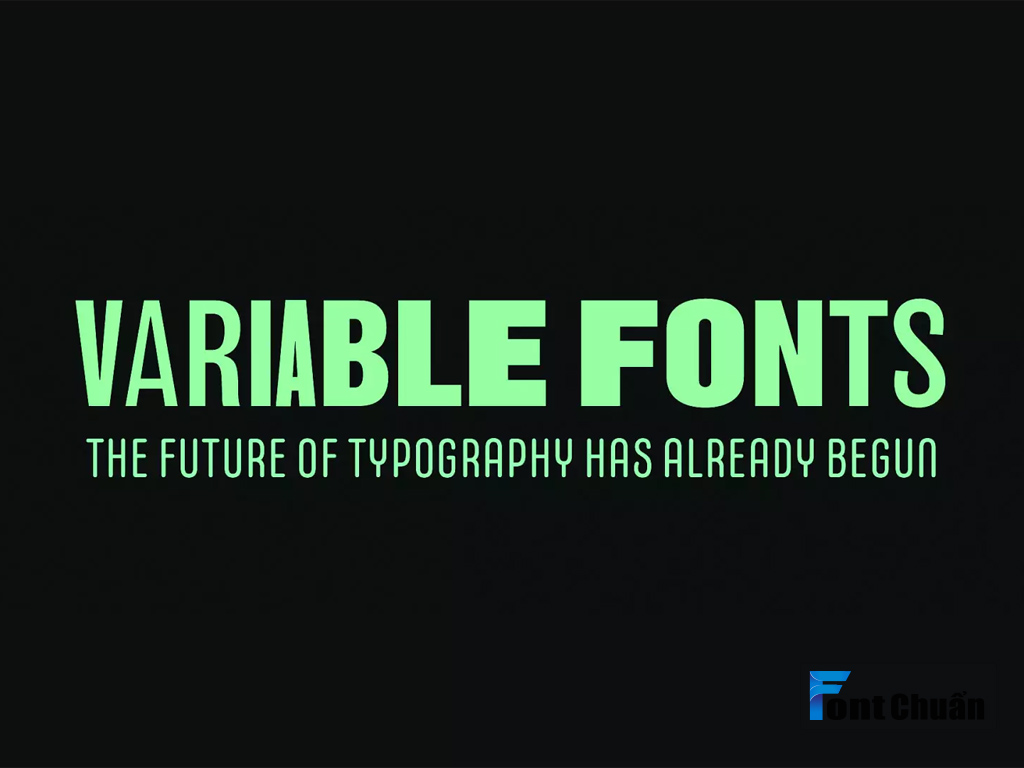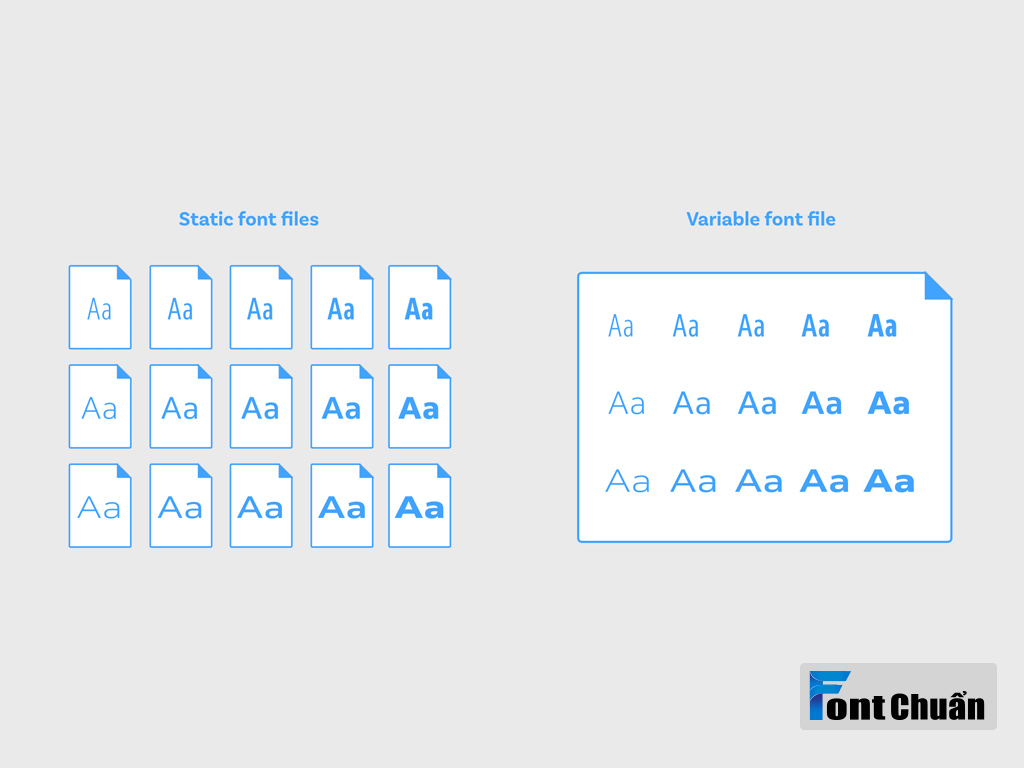
Variable Fonts cho phép tích hợp nhiều biến thể kiểu dáng như trọng lượng, độ rộng và độ nghiêng chỉ trong một tệp duy nhất, giúp tối ưu hiệu suất và linh hoạt hơn trong thiết kế. Được phát triển dựa trên chuẩn OpenType bởi Microsoft, Apple, Adobe và Google, công nghệ này mở ra tương lai mới cho responsive typography và thiết kế web hiện đại. Bài viết sau của Font Chuẩn sẽ đi sâu và tìm hiểu Variable Fonts là gì? Lợi ích, cách ứng dụng trong thiết kế, lập trình web và những lưu ý quan trọng khi triển khai.
Variable Fonts là gì? Định nghĩa chi tiết
Variable Fonts (phông chữ biến đổi) đánh dấu một bước tiến lớn của đặc tả OpenType, cho phép tích hợp nhiều biến thể kiểu dáng – như trọng lượng (weight), chiều rộng (width), độ nghiêng (slant) – chỉ trong một tệp duy nhất.
Khác với font tĩnh truyền thống yêu cầu nhiều file riêng biệt (Regular, Bold, Italic…), Variable Fonts tạo ra một phổ liên tục các phong cách, cho phép nhà thiết kế tùy chỉnh linh hoạt thông số như độ đậm chính xác (ví dụ 686/900) thay vì giới hạn ở các mức định sẵn.
Được phát triển từ sự hợp tác giữa Google, Apple, Microsoft và Adobe, công nghệ này giải quyết hạn chế cồng kềnh của font tĩnh và mở ra tương lai mới cho typography kỹ thuật số. Variable Fonts không chỉ tối ưu hiệu suất mà còn trao quyền sáng tạo mạnh mẽ hơn cho người dùng và nhà thiết kế.
Sự khác biệt giữa Variable Fonts và font tĩnh
Điểm khác biệt cơ bản giữa Variable Fonts và font tĩnh nằm ở cấu trúc tệp và khả năng biến đổi. Với font tĩnh, mỗi biến thể kiểu dáng như Regular, Bold hay Italic của một font (ví dụ Font chữ Roboto) yêu cầu tệp riêng biệt (Roboto-Regular.woff2, Roboto-Bold.woff2, Roboto-Italic.woff2). Trong khi đó, Variable Fonts như RobotoFlex.woff2 gói gọn toàn bộ biến thể vào một tệp duy nhất.
Không chỉ tối ưu về dung lượng và hiệu suất tải trang (giảm số lượng yêu cầu HTTP), Variable Fonts còn thay thế hệ thống kiểu rời rạc bằng các trục biến đổi (variation axes) như độ đậm (wght), độ rộng (wdth) và độ nghiêng (slnt). Người dùng có thể điều chỉnh linh hoạt giá trị trên các trục này, tạo ra vô số biến thể trung gian thay vì bị giới hạn ở các mức cố định.
Sự khác biệt này tác động sâu sắc đến thiết kế hiện đại:
- Hiệu suất web: Tệp gọn nhẹ, tối ưu tốc độ tải.
- Tự do sáng tạo: Dễ dàng tinh chỉnh typography theo yêu cầu thị giác.
- Responsive typography: Font thích ứng tốt hơn với kích thước và ngữ cảnh thiết bị.
- Biểu cảm typographic cao: Nhà thiết kế có thể kiểm soát tỉ mỉ độ đậm (ví dụ 451/900) hoặc chiều rộng, giúp giải quyết chính xác các vấn đề về bố cục, cân bằng hệ thống phân cấp thị giác và tối ưu trải nghiệm người dùng (UI/UX Design).
Variable Fonts không chỉ cải tiến hiệu quả kỹ thuật, mà còn mở ra một cách tiếp cận typography năng động và tích hợp sâu hơn vào thiết kế giao diện số.
Ưu điểm của việc sử dụng Variable Fonts
Việc áp dụng Variable Fonts mang lại nhiều lợi ích đáng kể so với việc sử dụng font tĩnh truyền thống, tác động tích cực đến cả hiệu suất kỹ thuật và khả năng sáng tạo trong thiết kế.
Tiết kiệm dung lượng, tăng tốc độ tải trang
Một trong những lợi ích lớn nhất của Variable Fonts là giúp giảm số lượng file font cần tải xuống. Thay vì phải sử dụng 4–5 file cho các kiểu chữ khác nhau (Regular, Bold, Italic, v.v.), giờ đây chỉ cần một file duy nhất. Điều này có thể làm giảm đáng kể tổng kích thước dữ liệu font phải tải, từ đó tăng tốc độ tải trang và tối ưu hóa hiệu suất website. Thực tế cho thấy trong những trường hợp font family lớn, việc gộp thành một variable font có thể giảm đến ~70% dung lượng so với sử dụng nhiều font tĩnh riêng lẻ. Kết quả là trang web nhẹ hơn, thời gian hiển thị nhanh hơn, cải thiện trải nghiệm người dùng.
Tùy biến linh hoạt về kiểu dáng chữ
Với Variable Fonts, nhà thiết kế có thể tùy chỉnh rất linh hoạt các thuộc tính chữ ngay trong một font. Bạn có thể điều chỉnh độ đậm, độ rộng, độ nghiêng liên tục theo những giá trị mong muốn, thay vì bị giới hạn ở vài mức cố định. Điều này cho phép tạo ra những biến thể chữ độc đáo, tinh chỉnh kiểu chữ sao cho phù hợp hoàn hảo với thiết kế mà không cần đổi font. Chẳng hạn, chỉ với một font, bạn có thể tinh chỉnh tiêu đề đậm hơn một chút và thu hẹp lại một chút cho vừa bố cục, trong khi văn bản thân bài vẫn ở độ đậm vừa phải – tất cả đều từ cùng một họ chữ. Sự linh hoạt này mở ra biên độ sáng tạo rất lớn cho designer trong việc thể hiện ý đồ thiết kế.
Thích ứng trên mọi thiết bị (Responsive Typography)
Variable Fonts giúp typography đáp ứng (responsive typography) trở nên khả thi và hiệu quả hơn. Nhờ khả năng biến đổi mượt mà, font chữ có thể tự điều chỉnh để phù hợp với nhiều kích thước màn hình và độ phân giải khác nhau. Ví dụ, trên màn hình nhỏ bạn có thể tăng nhẹ độ đậm hoặc kích thước quang học để chữ dễ đọc hơn, còn trên màn hình lớn chữ có thể mảnh mai tinh tế hơn. Các ký tự chữ có thể tự động thay đổi để tương thích với giới hạn của từng thiết bị và trình duyệt. Kết quả là nội dung được hiển thị nhất quán, đẹp mắt và dễ đọc trên mọi nền tảng – từ điện thoại, máy tính bảng cho đến desktop Retina. Đây chính là chìa khóa để thiết kế web đa thiết bị mà không phải tải nhiều font riêng cho từng trường hợp.
Thỏa sức sáng tạo và đảm bảo tính nhất quán
Variable Fonts cung cấp cho nhà thiết kế một công cụ mạnh mẽ để thử nghiệm sáng tạo. Bạn có thể khám phá vô số biến thể chữ từ một font duy nhất – điều trước đây đòi hỏi rất nhiều font khác nhau. Điều này đặc biệt hữu ích trong các dự án thiết kế thương hiệu hoặc poster, khi mà tính cá nhân hóa và độc đáo được đề cao. Ngoài ra, việc dùng một font biến đổi duy nhất cho toàn bộ dự án còn giúp đảm bảo tính nhất quán về phong cách chữ. Tất cả các biến thể (đậm, nghiêng, mở rộng, thu hẹp, v.v.) đều xuất phát từ cùng một bộ gene thiết kế, tránh sự lệch lạc khi phải kết hợp nhiều font khác nhau. Nhờ đó, tổng thể thiết kế sẽ hài hòa và chuyên nghiệp hơn.
>> Sử dụng ngay: Công cụ tạo 1000+ font chữ đẹp 𝖋𝖔𝖓𝖙𝖈𝖍𝖚𝖆𝖓.𝖈𝖔𝖒 – Copy ngay
Cách sử dụng Variable Fonts trong thực tế
Variable Fonts hiện đã được hỗ trợ rộng rãi trên cả phần mềm thiết kế đồ họa và các trình duyệt web hiện đại. Dưới đây là cách tận dụng công nghệ font chữ linh hoạt này trong thực tế:
Trong các phần mềm thiết kế đồ họa
Các ứng dụng thiết kế phổ biến như Adobe Photoshop, Illustrator, InDesign (phiên bản CC), cũng như các phần mềm khác như Sketch, Figma (mới), đã hỗ trợ Variable Fonts. Cách sử dụng trong các chương trình này thường khá đơn giản:
- Cài đặt font: Trước tiên, bạn cần cài đặt file Variable Font (thường định dạng .ttf hoặc .otf hoặc .woff2 cho web) vào hệ thống như cài font thông thường. Lưu ý chỉ cần một file cho toàn bộ họ font biến đổi, thay vì nhiều file.
- Chọn font: Mở ứng dụng thiết kế (Photoshop, Illustrator…), sử dụng công cụ Text (T) để tạo hộp văn bản và nhập nội dung. Trong bảng chọn font, tìm đến tên Variable Font vừa cài (thường sẽ có ký hiệu hoặc tên đặc trưng).
- Điều chỉnh trục biến thể: Khi một Variable Font được chọn, giao diện phần mềm sẽ cho phép bạn điều chỉnh các trục biến thể. Ví dụ trong Photoshop/Illustrator, sau khi chọn font, bạn sẽ thấy biểu tượng dấu VAR hoặc hai chữ T chồng ở bảng Character. Nhấp vào đó sẽ xuất hiện các thanh trượt (sliders) hoặc trường nhập cho từng trục (Weight, Width, Slant, v.v.). Bạn kéo thanh trượt hoặc nhập giá trị mong muốn để thay đổi kiểu chữ theo ý thích.
- Xem kết quả và tinh chỉnh: Kiểu chữ sẽ thay đổi ngay lập tức khi bạn điều chỉnh giá trị trục, cho phép xem trước kết quả trực quan. Hãy thử nghiệm các giá trị khác nhau cho đến khi đạt được kiểu dáng chữ ưng ý.
Trên web với CSS hiện đại (CSS Fonts Module Level 4)
Sử dụng Variable Fonts trong thiết kế web đòi hỏi khai báo @font-face trong CSS, tương tự như font web thông thường, nhưng có thêm một số thuộc tính mở rộng. Các trình duyệt hiện đại (Chrome, Firefox, Safari, Edge) đã hỗ trợ Variable Fonts theo tiêu chuẩn CSS Fonts Module Level 4, cho phép ta định nghĩa dải giá trị cho trục biến thể ngay trong @font-face.
Cách nhúng: Trước tiên, cần có file font định dạng web (nên dùng WOFF2 để đạt hiệu quả nén tốt nhất). Ví dụ, khai báo một Variable Font Roboto Flex với dải trọng lượng và độ rộng tùy chỉnh:
@font-face {
font-family: ‘Roboto Flex’;
src: url(‘RobotoFlex.woff2’) format(‘woff2’);
font-weight: 100 900; /* dải độ dày từ 100 đến 900 */
font-stretch: 75% 125%; /* dải độ rộng từ 75% đến 125% */
font-style: normal;
}
Ở ví dụ trên, thuộc tính font-weight: 100 900 và font-stretch: 75% 125% cho trình duyệt biết font này hỗ trợ trọng lượng từ 100 đến 900 và độ rộng từ 75% đến 125%. Nhờ đó, sau này trong CSS ta có thể đặt bất kỳ giá trị nào trong khoảng đó cho các phần tử HTML. Ví dụ:
h1 {
font-family: ‘Roboto Flex’, sans-serif;
font-weight: 700; /* chữ đậm cho tiêu đề */
font-stretch: 120%; /* hơi nới rộng chữ cho tiêu đề */
}
p {
font-family: ‘Roboto Flex’, sans-serif;
font-weight: 400; /* chữ thường cho đoạn văn */
font-stretch: 100%; /* độ rộng bình thường cho đoạn văn */
}
Như vậy, chỉ với một file font, ta có thể dùng cho cả tiêu đề và đoạn văn với trọng lượng khác nhau một cách linh hoạt. Ngoài cách dùng thuộc tính chuẩn (như font-weight, font-stretch như trên), CSS còn cung cấp thuộc tính font-variation-settings để điều khiển trực tiếp các trục theo tag (dùng cho các trục tùy chỉnh không có thuộc tính CSS tương ứng). Ví dụ: font-variation-settings: “wght” 350, “slnt” -10; sẽ đặt độ đậm là 350 và độ nghiêng -10 độ.
Tải ngay bộ sưu tập Font Việt Hóa mới cập nhật: TẠI ĐÂY
Thách thức và hạn chế của Variable Fonts
Dù mang lại nhiều lợi ích, Variable Fonts vẫn tồn tại một số thách thức cần lưu ý:
- Hỗ trợ trình duyệt không đồng đều: Một số môi trường cũ chưa hỗ trợ Variable Fonts đầy đủ, đòi hỏi nhà phát triển phải thiết lập fallback fonts để đảm bảo khả năng hiển thị ổn định. Tuy nhiên, tỷ lệ này đang giảm dần nhờ sự phổ biến của các trình duyệt hiện đại.
- Dung lượng file: Variable Fonts có thể lớn hơn một tệp font tĩnh nếu dự án chỉ sử dụng ít biến thể. Việc sử dụng hiệu quả cần cân nhắc dựa trên quy mô typographic yêu cầu.
- Độ phức tạp khi thiết kế: Việc tạo Variable Fonts yêu cầu kỹ thuật cao về glyph interpolation và font hinting để đảm bảo nội suy mượt mà và hiển thị sắc nét trên mọi kích thước.
- Hiệu năng render: Các hoạt động render font với giá trị trục động (ví dụ animation) đôi khi làm tăng tải cho trình duyệt, nhưng nhờ tối ưu hóa, ảnh hưởng này hiện khá nhỏ trong các hệ thống hiện đại.
Xu hướng phát triển của Variable Fonts
Variable Fonts đang dần trở thành xu hướng chủ đạo trong typography và thiết kế web, với ngày càng nhiều họ font hiện đại tích hợp định dạng này thay cho hệ thống file truyền thống. Các thư viện lớn như Google Fonts đã bổ sung hàng trăm font biến đổi, giúp nhà thiết kế dễ dàng tiếp cận và ứng dụng.
Về công nghệ, trình duyệt và phần mềm liên tục mở rộng hỗ trợ, với các cập nhật như thuộc tính font-optical-sizing trong CSS. Variable Fonts cũng truyền cảm hứng cho những sáng tạo mới như hoạt hình chữ, color fonts, và typography tương tác.
Bên cạnh đó, Parametric Fonts – dạng font cho phép tùy chỉnh sâu đặc tính hình học bằng thuật toán – đang được nghiên cứu như bước tiến tiếp theo. Tuy nhiên, Variable Fonts hiện vẫn là giải pháp phổ biến và thực tiễn nhất nhờ sự hỗ trợ rộng rãi và tính ổn định.
Tương lai, typography kỹ thuật số sẽ chứng kiến sự tích hợp sâu hơn của Variable Fonts, song song với những đột phá mới từ AI và công nghệ thiết kế generative.
Kết luận
Variable Fonts đánh dấu một sự thay đổi quan trọng trong typography kỹ thuật số. Chúng tối ưu hiệu suất web nhờ cấu trúc tệp đơn lẻ và giải phóng sức sáng tạo thông qua các trục biến đổi linh hoạt. Khả năng tạo ra các thiết kế đáp ứng, dễ đọc và năng động hơn khiến Variable Fonts trở thành công cụ thiết yếu, định hình tương lai của trải nghiệm người dùng trên môi trường số.